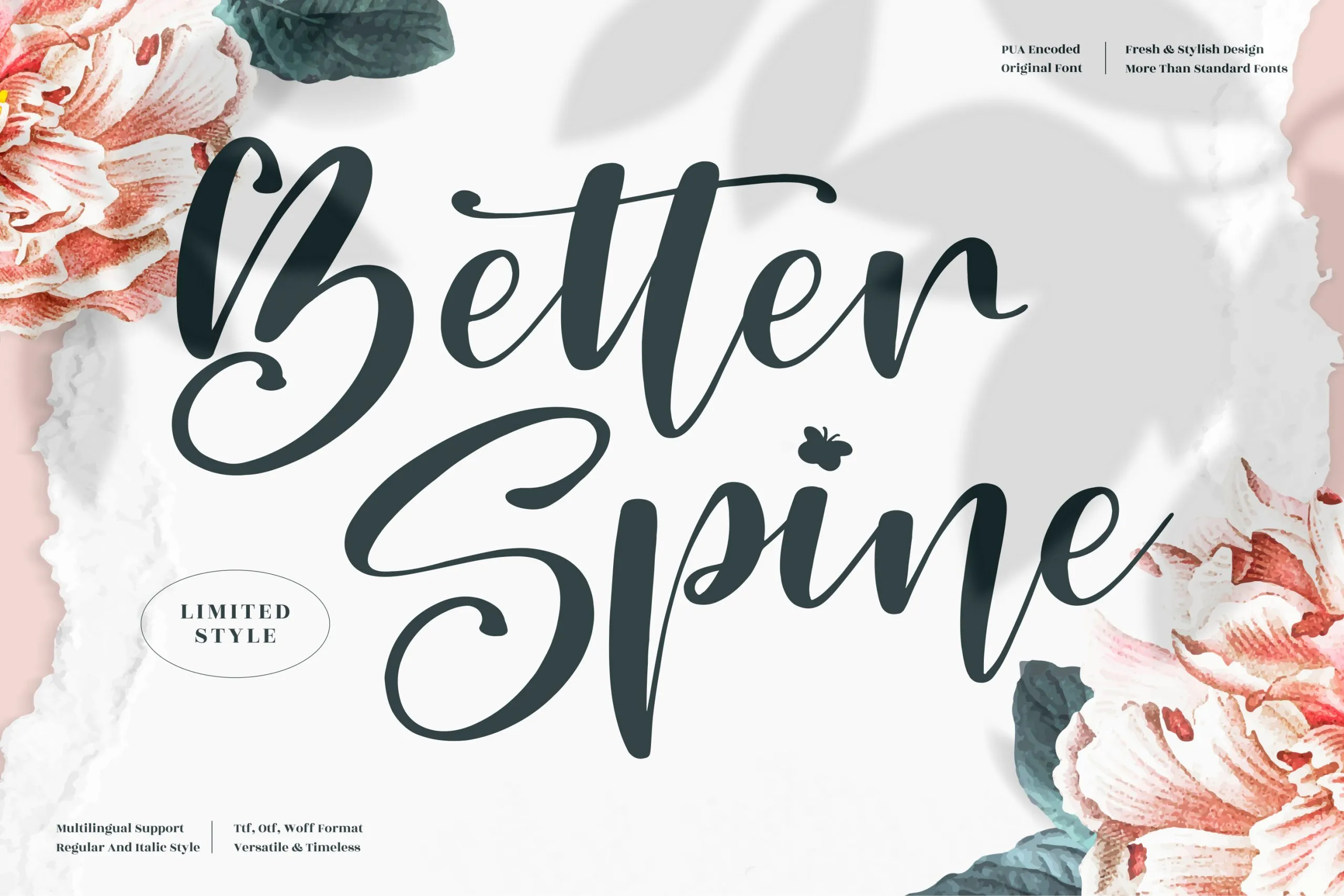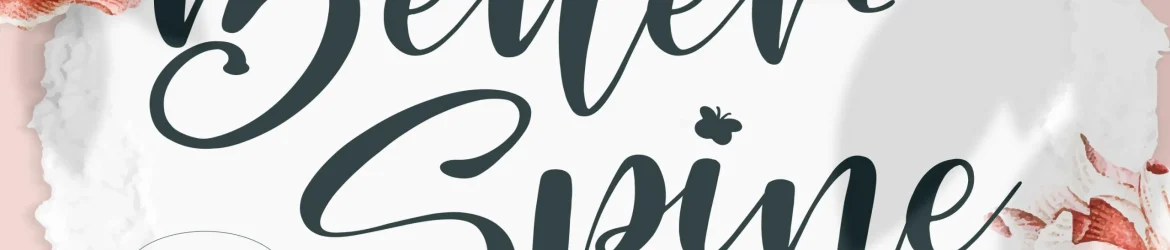
Better Spine Font – Download Grátis
Esta é uma fonte de calligrafia romântica perfeitamente adaptada para um amplo range de projetos. Ela faz maravilhas quando se trata de logotipos, identidade visual, designs de mobiliário, embalagens de produtos, talheres, frases, postais, sacolas de shopping, camisetas personalizadas, capas de livros, cartões de nome, convites, cartas de agradecimento, rótulos, fotografia e até mesmo marcos especiais. Se você está à procura de um toque poético em seu design gráfico, este é o lugar para começar. A melhor parte? Esta fonte também se destaca como uma opção perfeita para qualquer projeto que precise de um sabor de escrita bonita e elegante. Com certeza, vai tornar a sua experiência no Better Spine Font mais suave e sofisticada.